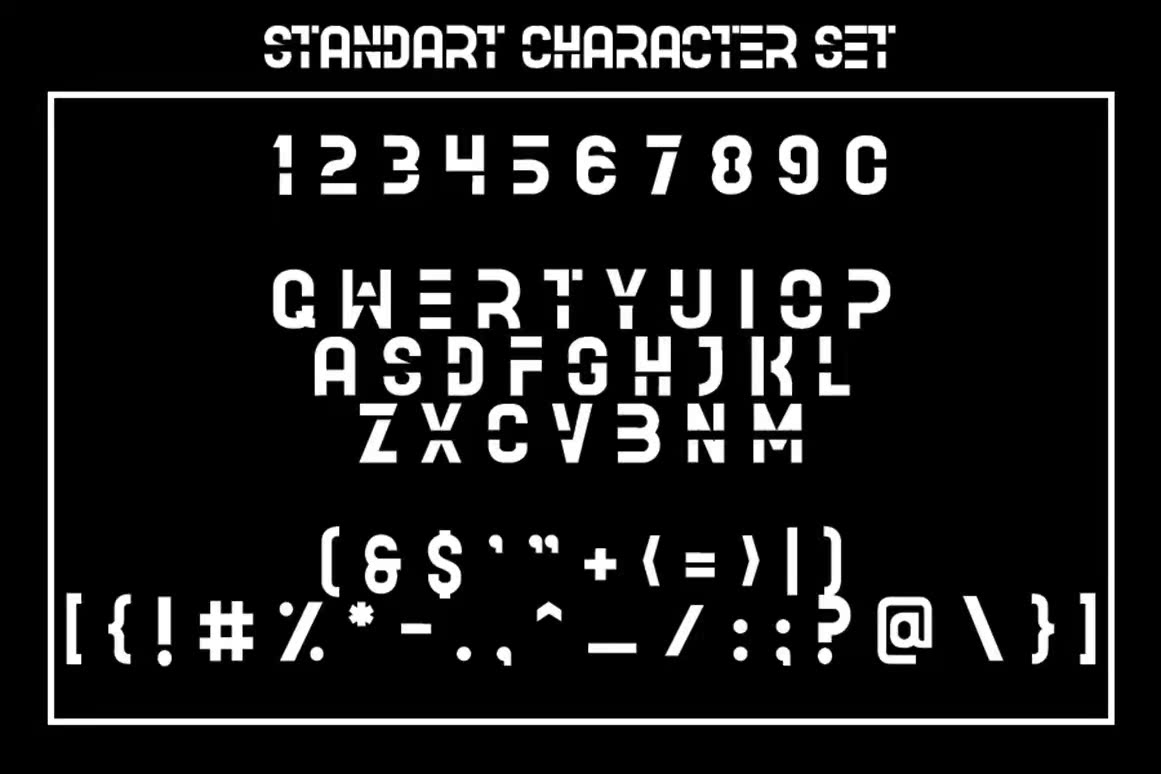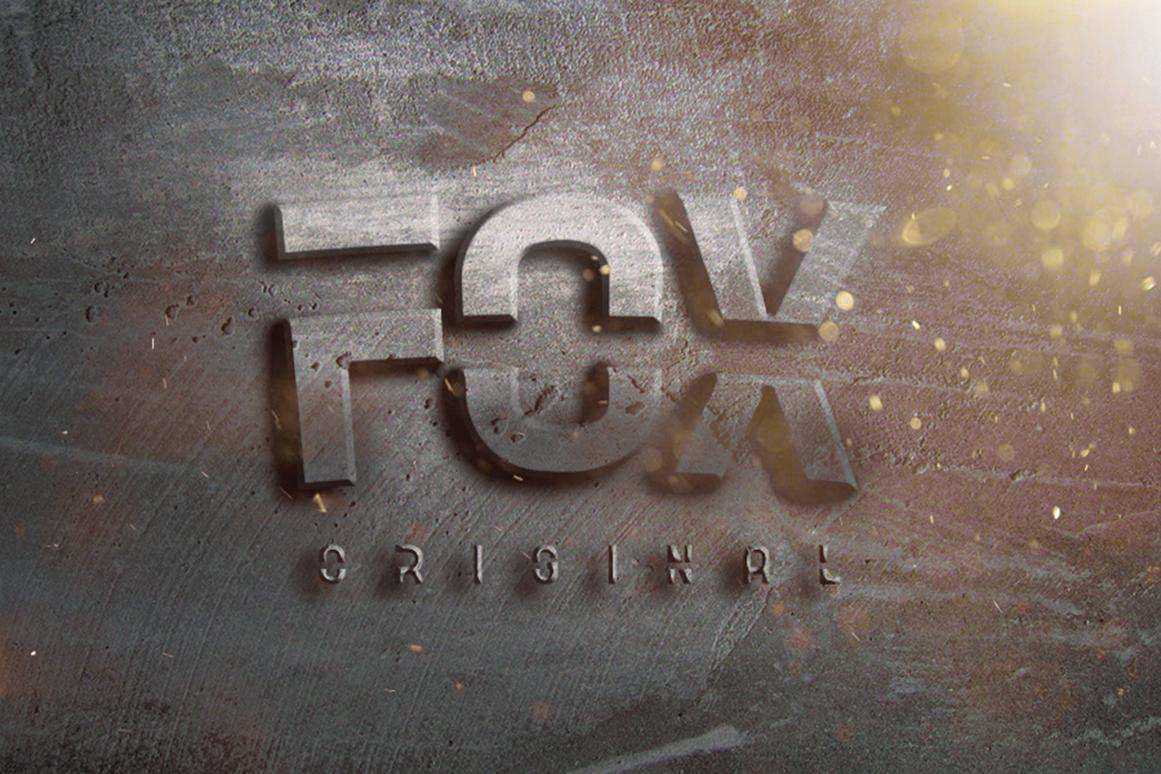
Brokernisacool,Interestings and BoldDisplayFont。专业设计的Tomakey Your Creation Look of This World,此Font有可能进一步提升您的创意。Brokernisacool,Interestings and BoldDisplayFont。专业设计的Tomakey Your Creation Look of This World,此Font有可能进一步提升您的创意。